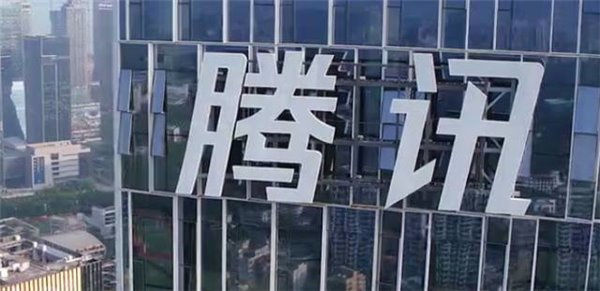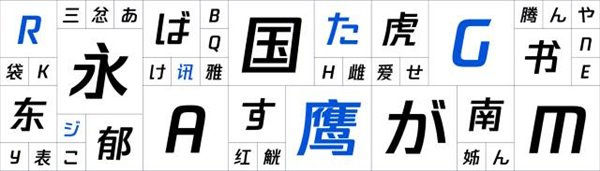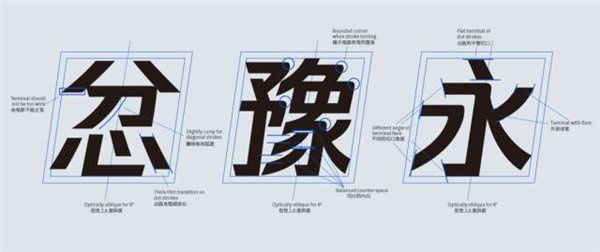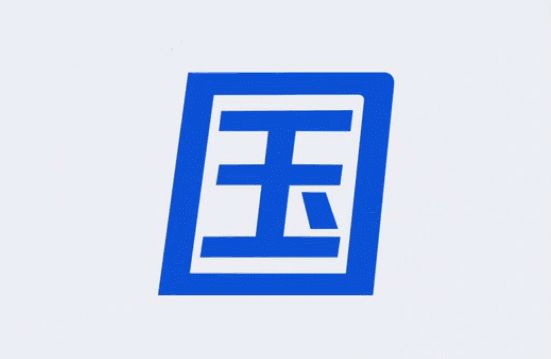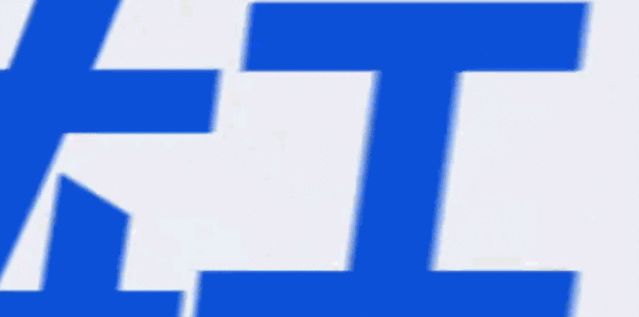
腾讯大楼上的腾讯Logo悄悄地发生了一些变化,实际上,新logo使用了腾讯昨天发布的“腾讯字体”( TTTGB-Medium ) ,据腾讯介绍,新字体更现代、更协调、更动感。
据悉,腾讯字体收录 6,763全形汉字,以及拉丁字母、希腊字母、日文平假名及片假名字母、俄语西里尔字母,由全球知名字体公司 Monotype 的字体设计师小林章提供指导,字体设计师许瀚文主导中文部分,日文字体设计师土井辽太负责日语假名设计,拉丁文字体设计师 Steve Matteson、Juan Villanueva 也参与了汉字以外的字型设计。
这套字体最不同寻常的地方在于全部是斜体,更准确地说,这是第一套完整支持GB 2312-80简体中文编码字符标准的“真斜体”。其实,腾讯一直以来都对斜体情有独钟,原先的斜体logo就用了19年之久。腾讯官方称,斜体有一种向前的意味,自带动感和速度感,是一种奔跑的姿态。在我们看来,这体现了腾讯一种带领科技潮流的信心和梦想。
腾讯字体最终敲定的方案是:汉字的视觉倾斜度为8°,辅以一定的视觉修正,内白设计成平衡均匀,中宫也是以平均为主,确保能够像其他中文字型般使用。为了配合中文,拉丁文字的视觉倾斜度为10°。
除了斜体,腾讯字体还有一个重要特征,就是切角。在充分衡量了字体的视觉平衡性以后再加上切角,比如说在非重要笔划的末端、横笔的两端、竖笔的顶部等。